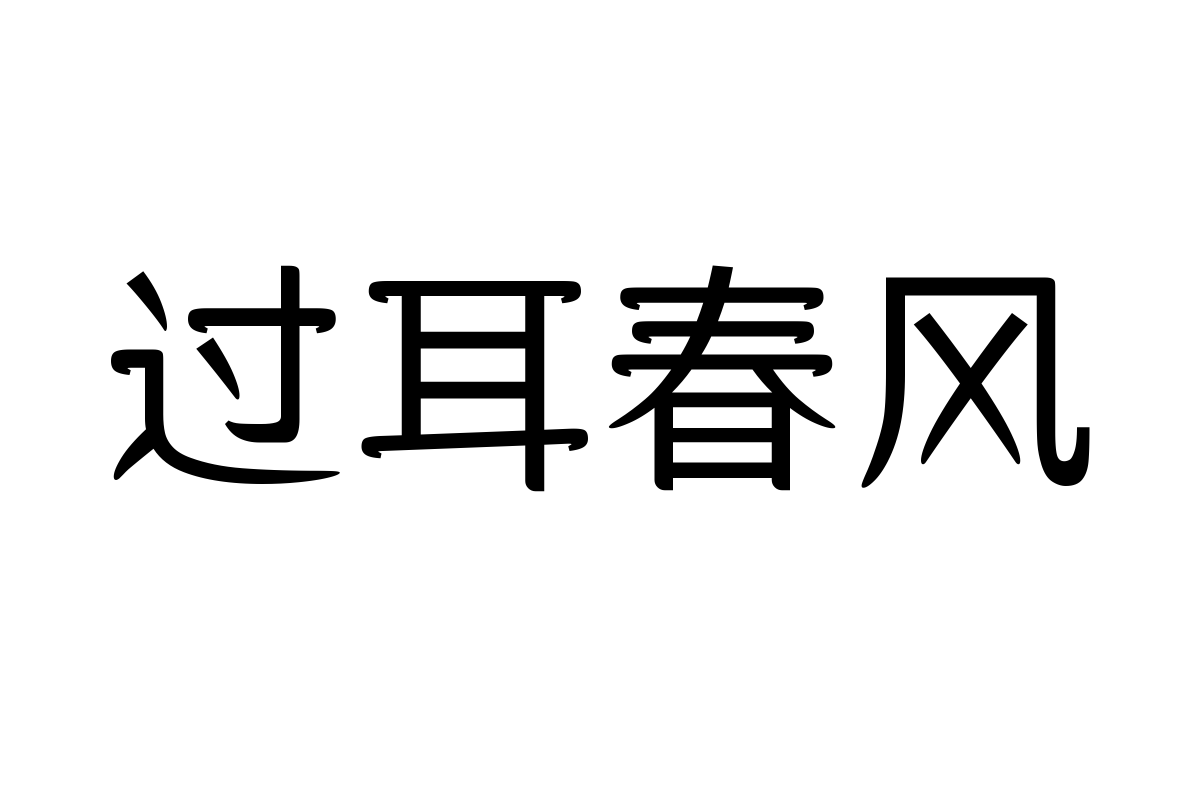
三极欢乐逗牛体是一款中文字体,由北京华文字库有限公司设计。这款字体以其独特的字形和风格而受到欢迎,适用于各种需要使用中文字体的场合。
三极欢乐逗牛体的笔画粗细适中,结构紧凑,给人一种简洁明快的感觉。它的字形特点包括:横平竖直、撇捺舒展、点画分明等。这种字形特点使得汉字在视觉上更加清晰易读,同时也增加了字体的美感。
此外,三极欢乐逗牛体还采用了一些现代的设计元素,如斜线、曲线等,使得字体更加活泼有趣。这使得它在广告、包装、杂志等场合中得到了广泛的应用。
总的来说,三极欢乐逗牛体是一款具有独特风格和美感的中文字体,适合用于需要展示个性和创意的场合。